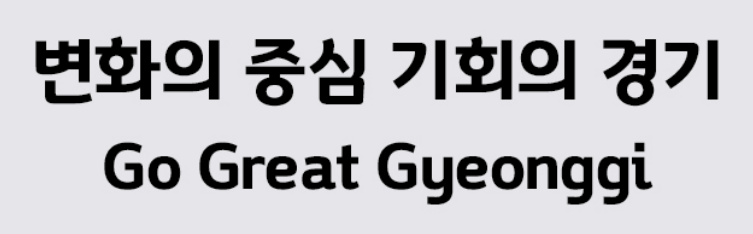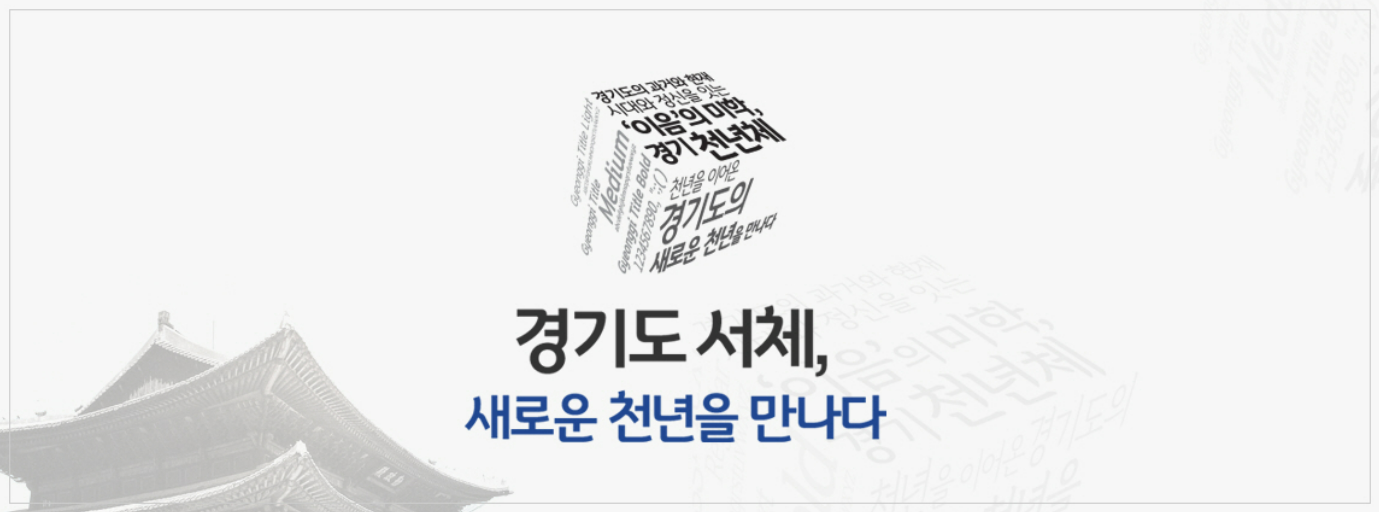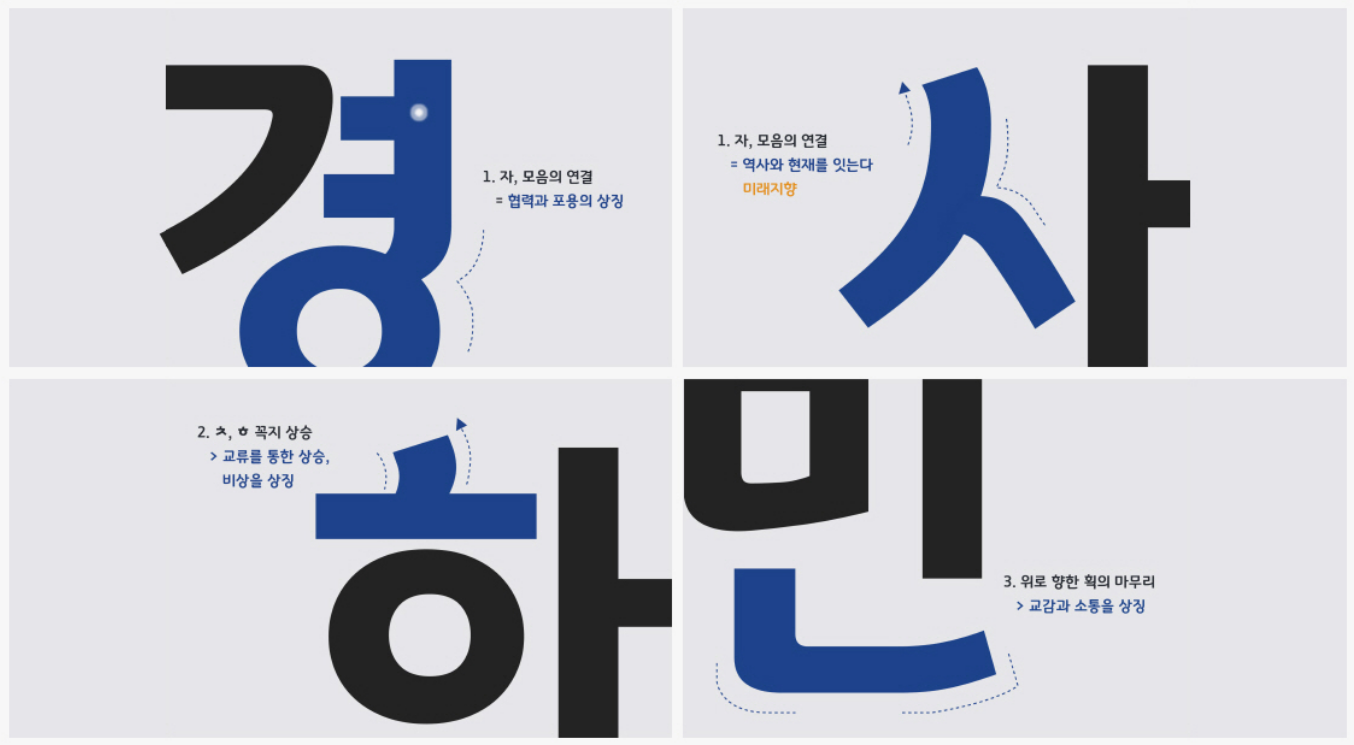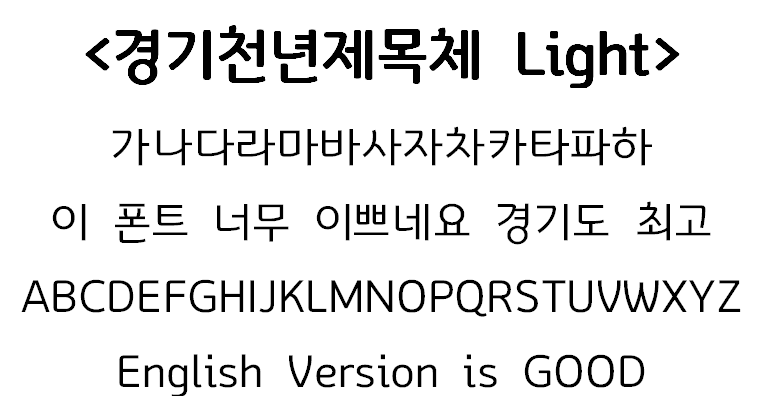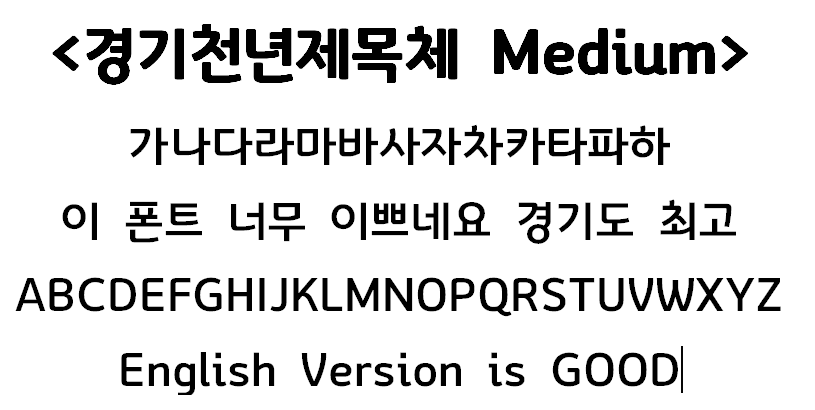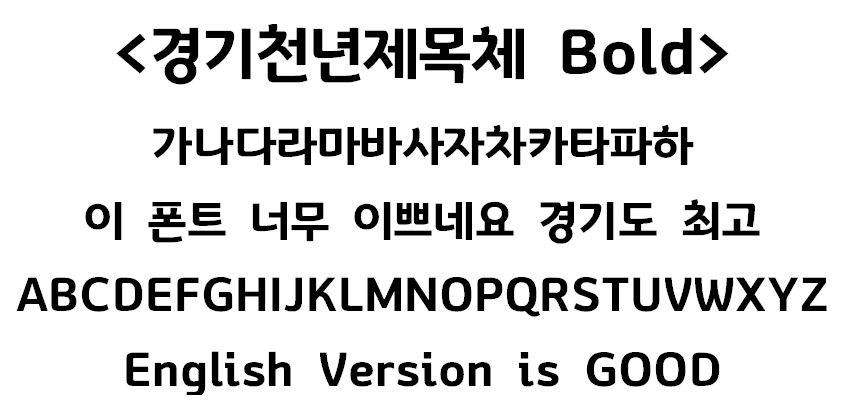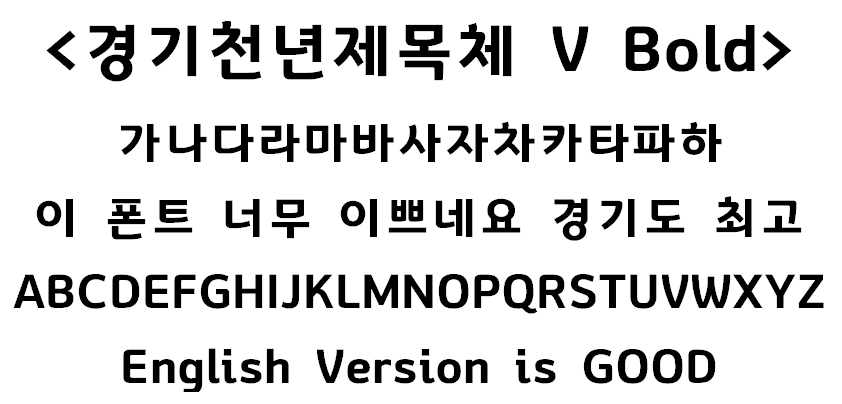
경기도의 정체성을 강화하고자 경기도에서 만든 경기도 서체를 소개합니다. 천년을 이어온 경기도의 역사를 기리고 역사적, 지리적, 사회적, 문화적 특성을 시각화한 글씨체 폰트입니다. 요즘 관공서나 기업 그리고 대학교에서 많이 사용되고 있는 글씨체입니다. 윈도우 버전과 맥 버전으로 따로 다운로드할수 있게 해두었으니 필요한 분들은 가장 아래 부분에서 다운로드 받으시기 바랍니다.
경기천년제목체 소개
자음과 모음을 자연스럽게 연결하고, 협력과 포용을 상징하는 경기도 서체는 과거와 현재 그리고 미래를 잇는다는 의미를 담고 있습니다. 영문은 한글을 특성을 그대로 가져갈 수 있도록 우아한 곡선과 절체된 직선이 특징입니다.
경기천년제목체 Light
경기천년제목체 Light 타입 예시 입니다. 글씨를 썼을때 이런 느낌입니다.
경기천년제목체 Medium
경기천년제목체 Medium 타입 예시입니다. 글씨를 타이핑하면 이런 느낌입니다.
경기천년제목체 Bold
경기천년제목체 Bold 타입 입니다. 아래는 예시입니다.
경기천년제목체 V_Bold
경기천년제목체 V_Bold 버전의 글씨체 입니다. 아래 예시입니다.